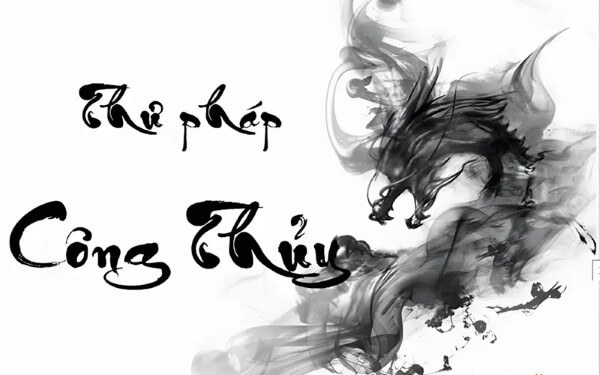
Font chữ thư pháp là kiểu chữ mô phỏng nghệ thuật viết thư pháp truyền thống, mang những đường nét mềm mại, uyển chuyển, thể hiện tinh thần tự do, phóng khoáng của người nghệ sĩ. Trong thiết kế hiện đại, font chữ thư pháp thường được ứng dụng trong thiệp cưới, bìa sách, tiêu đề, hay các tác phẩm nghệ thuật số để tôn lên vẻ sang trọng, đậm chất văn hóa phương Đông.
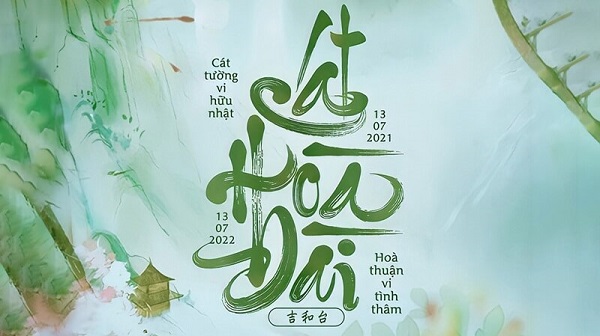
Từ lâu, thư pháp đã là một phần không thể thiếu trong đời sống tinh thần của người Á Đông. Ở Việt Nam, nét chữ thư pháp không chỉ là công cụ truyền tải ngôn từ mà còn là cách thể hiện tâm hồn, cảm xúc và phong thái của người viết. Ngày nay, với sự phát triển của công nghệ, bạn có thể dễ dàng sở hữu những font chữ thư pháp Việt hóa độc đáo, giúp tái hiện trọn vẹn tinh thần nghệ thuật truyền thống trong từng thiết kế.
Top 8+ font chữ thư pháp đẹp và ấn tượng nhất
1. Font VN Lovelista
Font VN Lovelista là lựa chọn hoàn hảo cho những ai yêu thích phong cách nhẹ nhàng, thanh thoát. Font mang những đường nét mềm mại, uốn lượn tinh tế, xen kẽ giữa nét thanh và nét đậm tạo nên cảm giác hài hòa, duyên dáng.
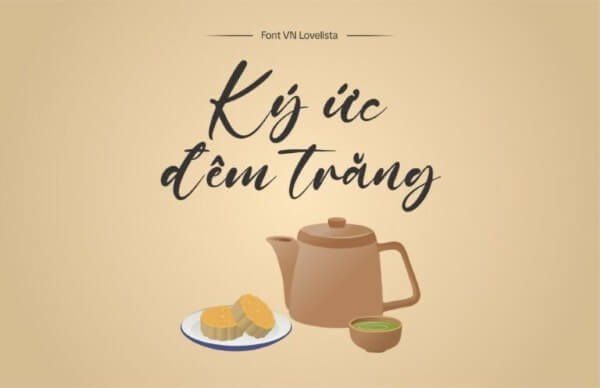
Nhờ sự tinh tế ấy, font chữ thư pháp VN Lovelista được ưa chuộng trong thiết kế thiệp cưới, thiệp mừng, câu đối, bìa sách hay tranh thư pháp số. Các nhà thiết kế yêu thích font này bởi khả năng truyền tải cảm xúc sâu sắc, vừa mang nét truyền thống Việt, vừa hiện đại, dễ đọc và cuốn hút.
2. Font VN Opulent Brush
VN Opulent Brush là sự hòa quyện giữa sức mạnh và sự phóng khoáng. Từng nét chữ mang hơi thở của nghệ thuật ông đồ xưa, mạnh mẽ mà vẫn uyển chuyển. Font này thường được dùng trong các thiết kế mang tính nghi lễ hoặc trang trọng như câu đối Tết, biển hiệu thư pháp, hoặc các ấn phẩm văn hóa.
Người dùng yêu thích tải phông chữ thư pháp miễn phí Opulent Brush bởi khả năng tái hiện chân thật nét cọ truyền thống, giúp tác phẩm toát lên vẻ cổ điển, trang nghiêm nhưng vẫn mang tính thẩm mỹ cao.
3. Font Bendigo Việt Hóa
Nếu bạn cần sự tỉ mỉ, sang trọng và thanh lịch, font chữ thư pháp Việt hóa Bendigo là lựa chọn tuyệt vời. Bộ font này nổi bật với những chữ hoa cách điệu tinh tế, rất thích hợp cho thiết kế thương hiệu, logo, chứng chỉ, thiệp mời hoặc sổ tay nghệ thuật.
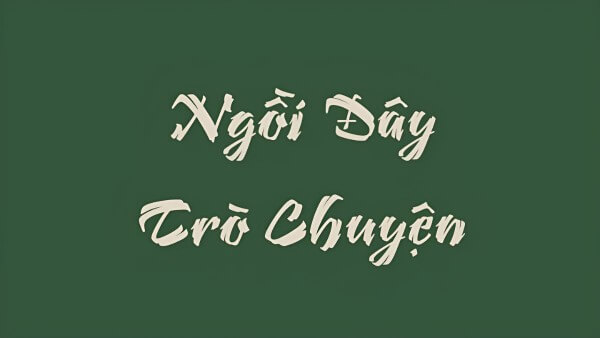
Các nhà thiết kế đánh giá cao Bendigo bởi khả năng mang lại cảm giác cân bằng giữa truyền thống và hiện đại, giúp các sản phẩm mang tính thẩm mỹ cao mà vẫn gần gũi, thân thiện với người Việt.
4. Font LNTH Watermark
Font LNTH Watermark mang đến cảm giác an yên, nhẹ nhàng với những đường nét thanh mảnh và tinh tế. Đây là một font chữ thư pháp lý tưởng cho các thiết kế liên quan đến thiền, tâm linh hoặc nghệ thuật Phật giáo.
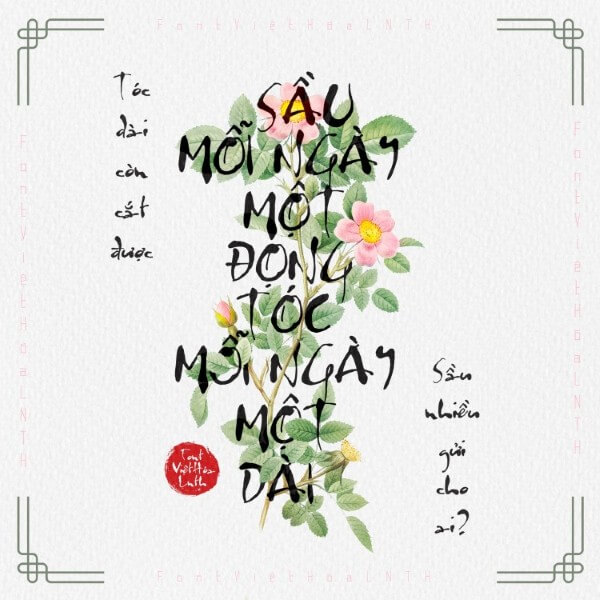
Nhờ phong cách nhẹ nhàng và tĩnh tại, LNTH Watermark thường xuất hiện trong sách kinh, bìa kệ, tranh phong thủy hay poster mang chủ đề thiền định. Font này giúp người xem cảm nhận được sự thanh thoát và bình yên trong tâm hồn.
5. Font LNTH Dieter Steffmann
Font Dieter Steffmann là sự pha trộn giữa nét trẻ trung và truyền thống. Các đường nét mềm mại, tinh tế nhưng không kém phần trang trọng khiến nó trở thành một trong những font chữ thư pháp được yêu thích nhất hiện nay.
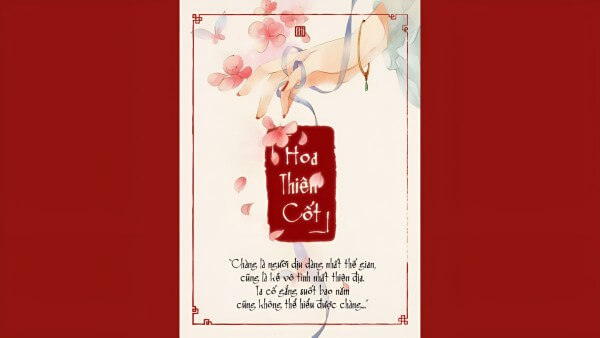
Người dùng thường áp dụng font này trong thiệp mừng, thư chúc, hoặc các thiết kế lễ hội gia đình. Sự kết hợp giữa uyển chuyển và vững vàng khiến Dieter Steffmann phù hợp cho cả mục đích cá nhân lẫn thương mại – đặc biệt là trong thiết kế bìa sách và quà tặng thủ công.
6. Font Thành Công
Font Thành Công thể hiện tinh thần sáng tạo và mạnh mẽ, mang phong cách hiện đại nhưng vẫn giữ hồn cốt truyền thống. Những nét chữ đậm, sắc sảo của font này giúp tạo điểm nhấn trong các ấn phẩm quảng cáo, bao lì xì hoặc bìa sách.
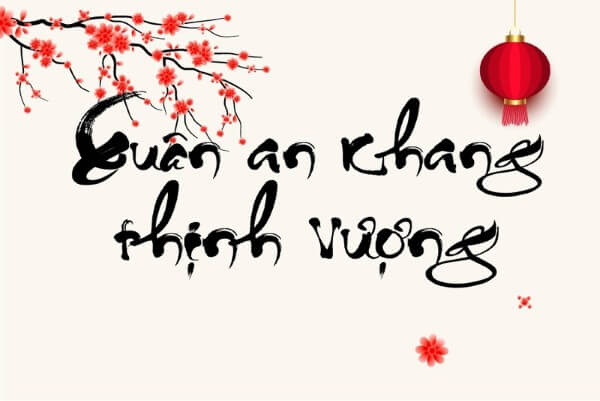
Đây là một phông chữ miễn phí thư pháp được yêu thích bởi các nhà thiết kế muốn mang lại cảm giác “đông phương huyền bí” nhưng vẫn hiện đại, phù hợp cho cả sản phẩm văn hóa lẫn thiết kế thương mại.
7. Font MTD Geza Script
Geza Script là sự kết hợp hài hòa giữa nét viết tay tự nhiên và tinh thần thư pháp truyền thống. Font này dễ đọc, đường nét sắc sảo, rất thích hợp cho các thiết kế logo, bìa sách hay poster quảng cáo.
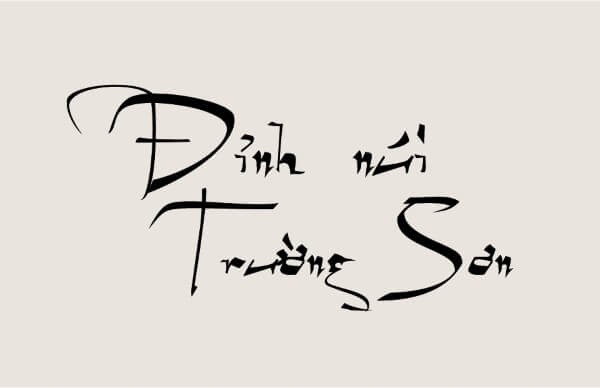
Không chỉ vậy, Geza Script còn được ưa chuộng trong thiết kế nội thất, trang trí văn phòng hoặc các sự kiện văn hóa, nơi cần tạo cảm giác trang trọng và chuyên nghiệp. Sự đa dụng khiến font này trở thành một trong những lựa chọn hàng đầu trong danh sách font chữ thư pháp đẹp.
8. Font SVN Hottroof Semhesta
SVN Hottroof Semhesta mang phong cách thư pháp nhẹ nhàng, tinh tế. Font này được ví như “làn gió tĩnh lặng” trong thế giới thiết kế – vừa thiền định, vừa sâu lắng.
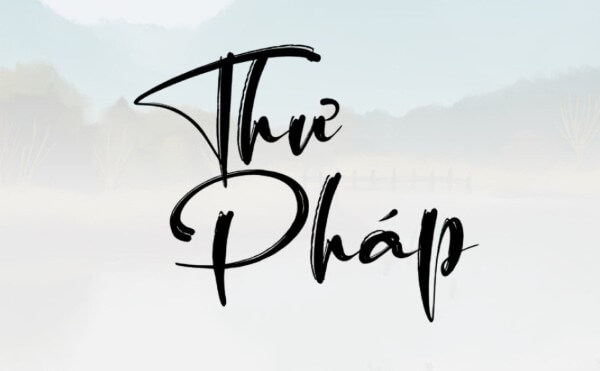
Nó phù hợp cho các ấn phẩm tôn giáo, sách kinh, tranh thư pháp số hoặc tài liệu thiền học. Nhiều nhà thiết kế sử dụng font này để tạo không gian an nhiên, giúp người xem cảm nhận được vẻ đẹp của tĩnh tại và bình tâm trong cuộc sống bận rộn.
9. Font Tiểu Tự
Font Tiểu Tự mang hơi hướng nghệ thuật cổ điển, được tạo nên từ sự pha trộn giữa nét đậm và nét mảnh. Từng chữ cái trong font đều có sự uyển chuyển và mềm mại, giúp tạo nên những thiết kế mang đậm dấu ấn cá nhân.